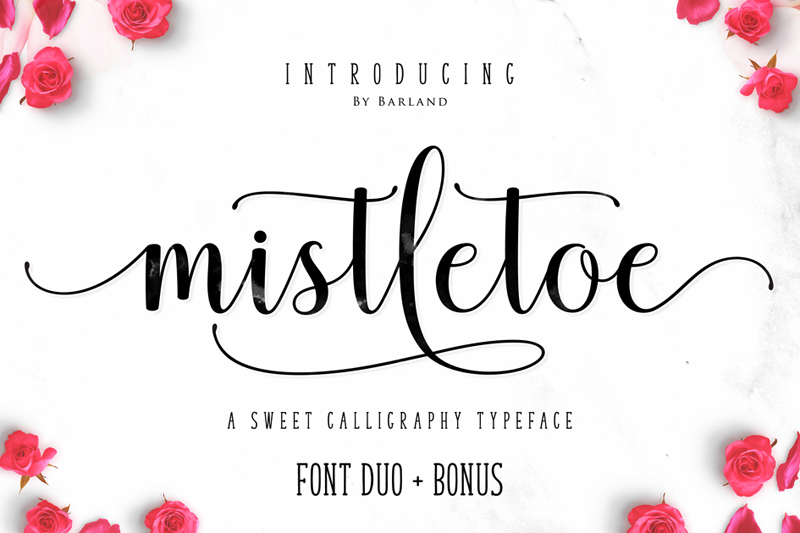
Esta Mistletoe Script Font é uma bela introdução ao design do designer Barland, especializado no gênero de fonts Calligraphy. Desenvolvida como uma combinação única e inovadora entre elementos clássicos e modernos, essa font se destaca por sua estética íntima, que transmite um estilo único e imperfeito. As letras têm a leveza e claridade dos movimentos de dança, proporcionando um equilíbrio elegante entre formas suaves e simplicidade. Com o seu design versátil, esta font se torna uma escolha perfeita para vários usos, incluindo celebrações como casamentos e eventos, cartas de convite, cartões de presente de acompanhamento, números de mesa em festas, menu de aperitivos com cabeçalhos, desenhos para exposições, logotipos, carrosel de blogs personalizados, endereços customizados, selos e embalagens. É uma ferramenta ideal para quem busca trazer um toque único à sua arte visual ou design.